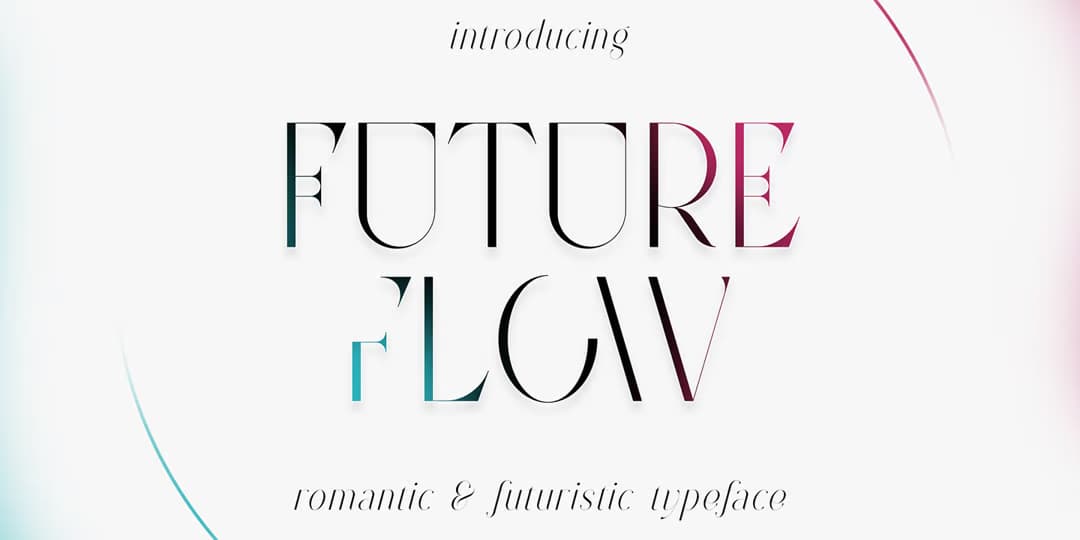
Future Flow
繊細でスタイリッシュなモダンローマンディスプレイ。ヘアラインが非常に繊細なライトウェイトのモダンローマンをベースに、様々なスタイルのグリフがファミリーになったディスプレイ。普通の Regular の他、ストロークの端が切り落とされた Cut、ストロークの接続部が欠けた Stencil、ストロークそのものが大胆に欠けた Display、一部のストロークが二重になった Two Line、グリフ内に斜めのヘアラインが走る Line、開口部が閉じたりエレメントが二重になったりと大胆なアレンジが施された Futuristic の7種がある。Regular のみ小文字と Italic があり、他は大文字のみ。本日は映画『バック・トゥ・ザ・フューチャー』シリーズでドクを演じたクリストファー・ロイド Christopher Lloyd の誕生日(1938)なので Future な書体を紹介してみた。